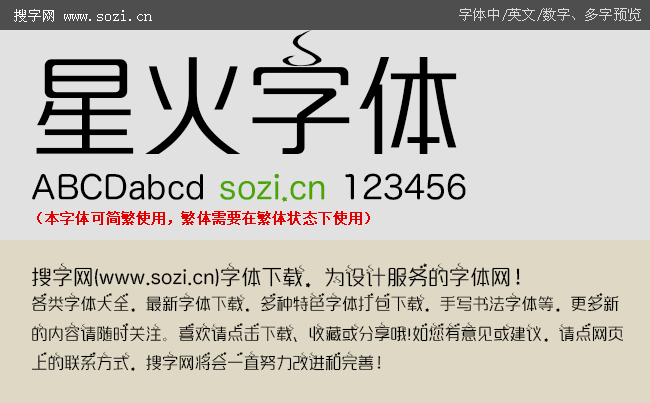
星火字體
搜字網(wǎng)給大家提供一款星火字體手機(jī)中文字體下載。這款手機(jī)字體是將黑體字體進(jìn)行重新設(shè)計(jì),更加具有藝術(shù)感,字體間又嵌入了卡通圖案。是一款非常藝術(shù)的字體,特別適合喜歡手機(jī)字體個(gè)性一些的朋友在手機(jī)上安裝使用。